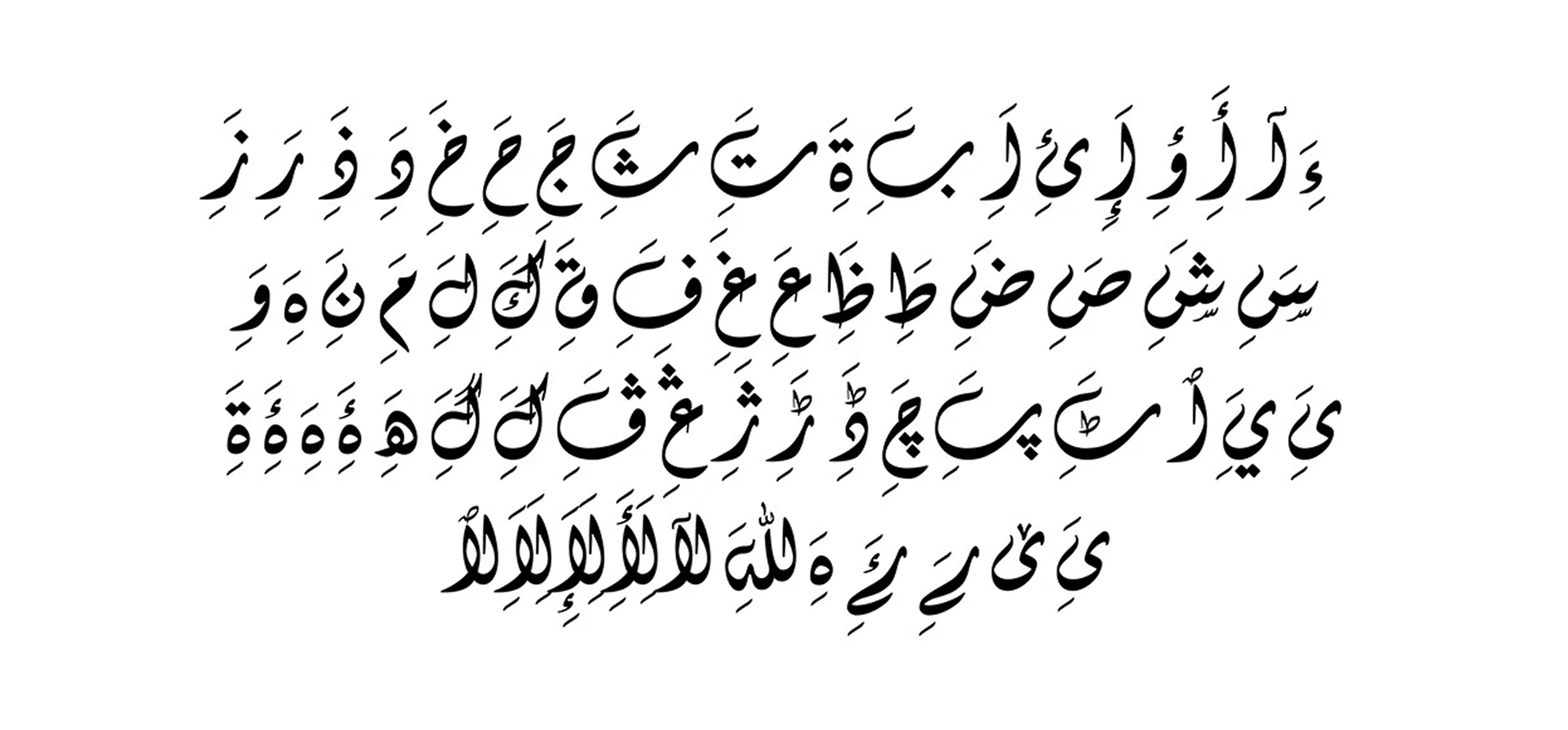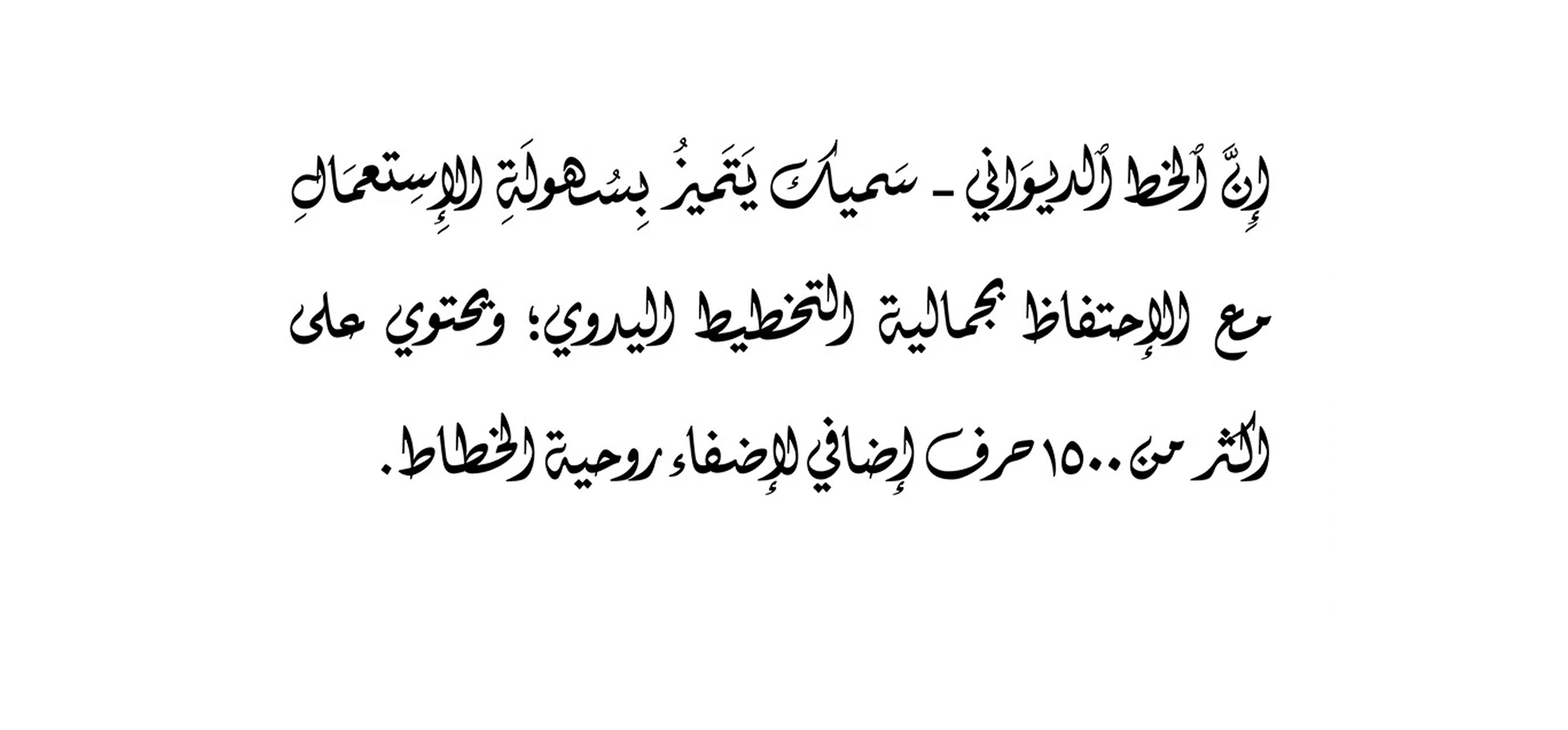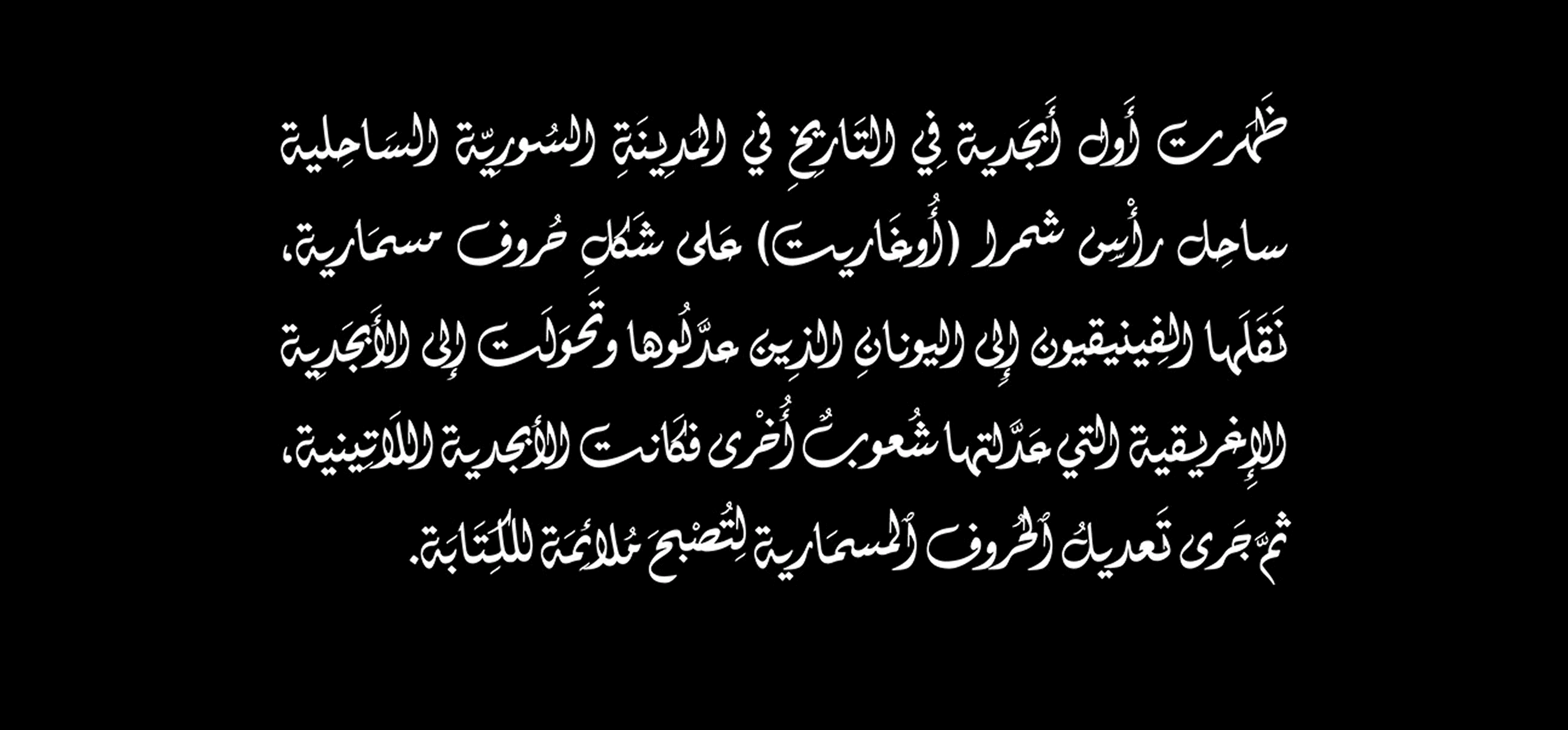
الخط JH Diwani Simplified Black هو خط عربي متقدم يُحاكي الخط الديواني بأدق تفاصيله. يُستخدم عادةً في بطاقات الزواج / التهنئة، العناوين الرئيسية، الشعر، والكتب.
يرجى ملاحظة أن خاصية الكشيدة العربية غير متوفرة في هذا الخط.
الخط JH Diwani Simplified Black هو خط عربي متقدم يُحاكي الخط الديواني بأدق تفاصيله. يُستخدم عادةً في بطاقات الزواج / التهنئة، العناوين الرئيسية، الشعر، والكتب.
يرجى ملاحظة أن خاصية الكشيدة العربية غير متوفرة في هذا الخط.
الخط JH Diwani Simplified Black هو خط عربي متقدم يُحاكي الخط الديواني بأدق تفاصيله. يُستخدم عادةً في بطاقات الزواج / التهنئة، العناوين الرئيسية، الشعر، والكتب.
يرجى ملاحظة أن خاصية الكشيدة العربية غير متوفرة في هذا الخط.